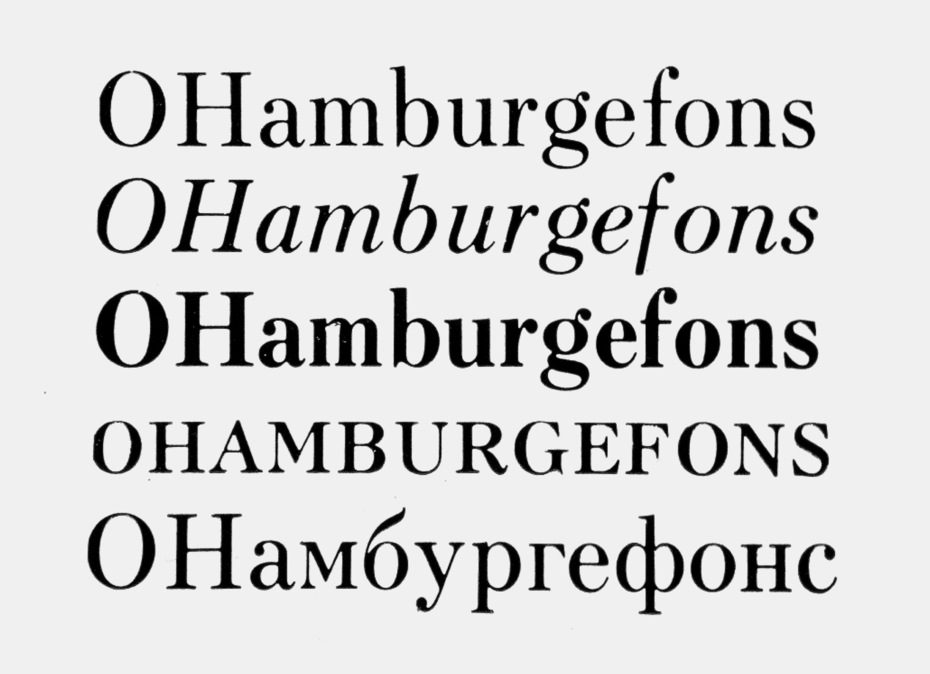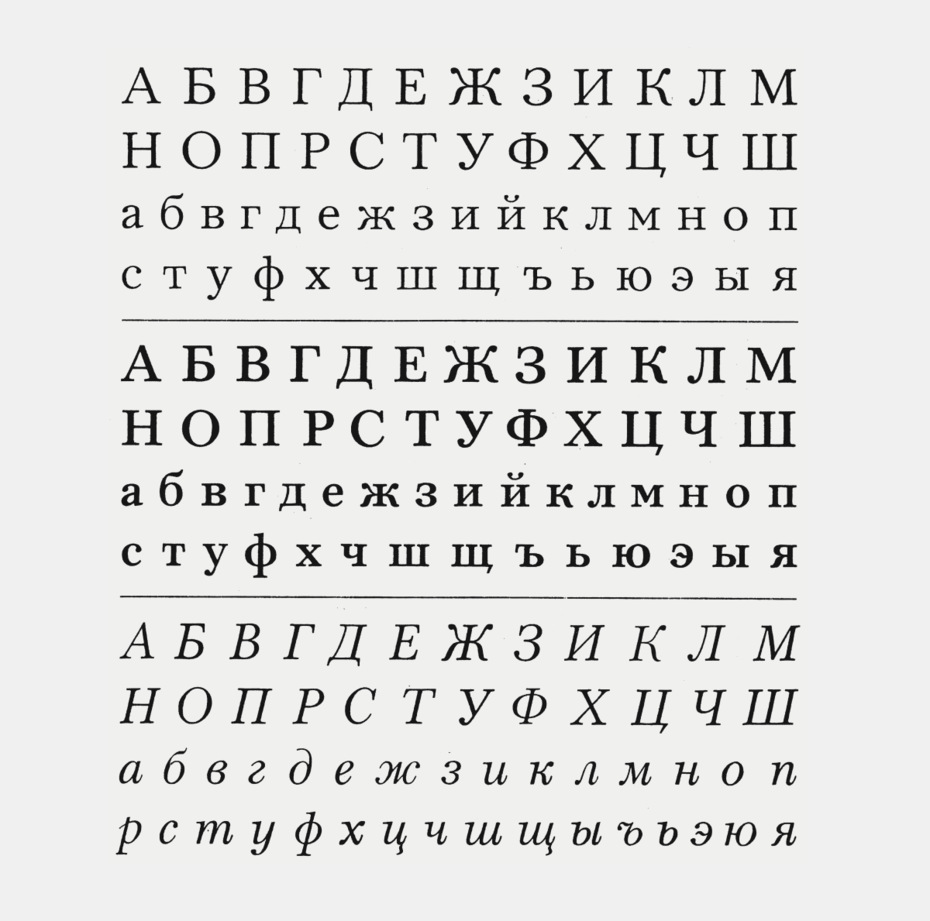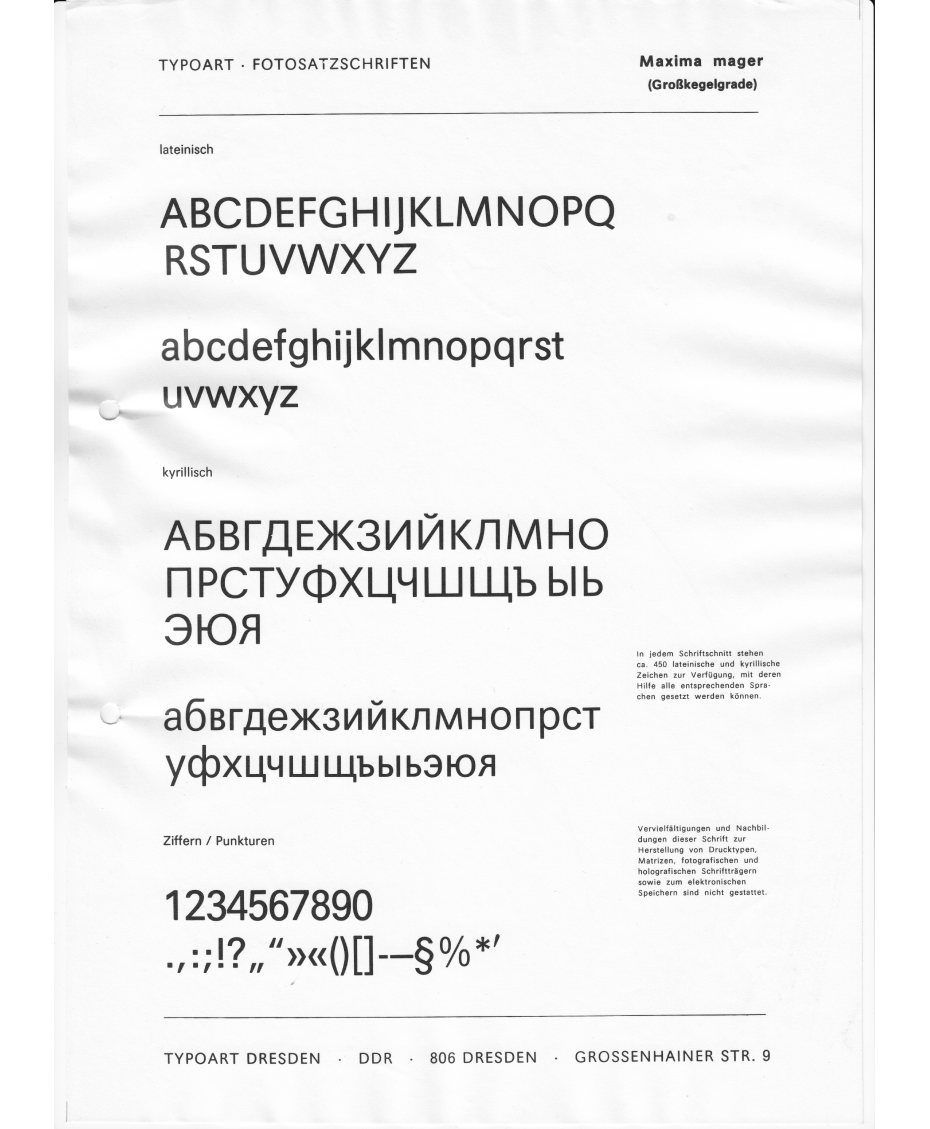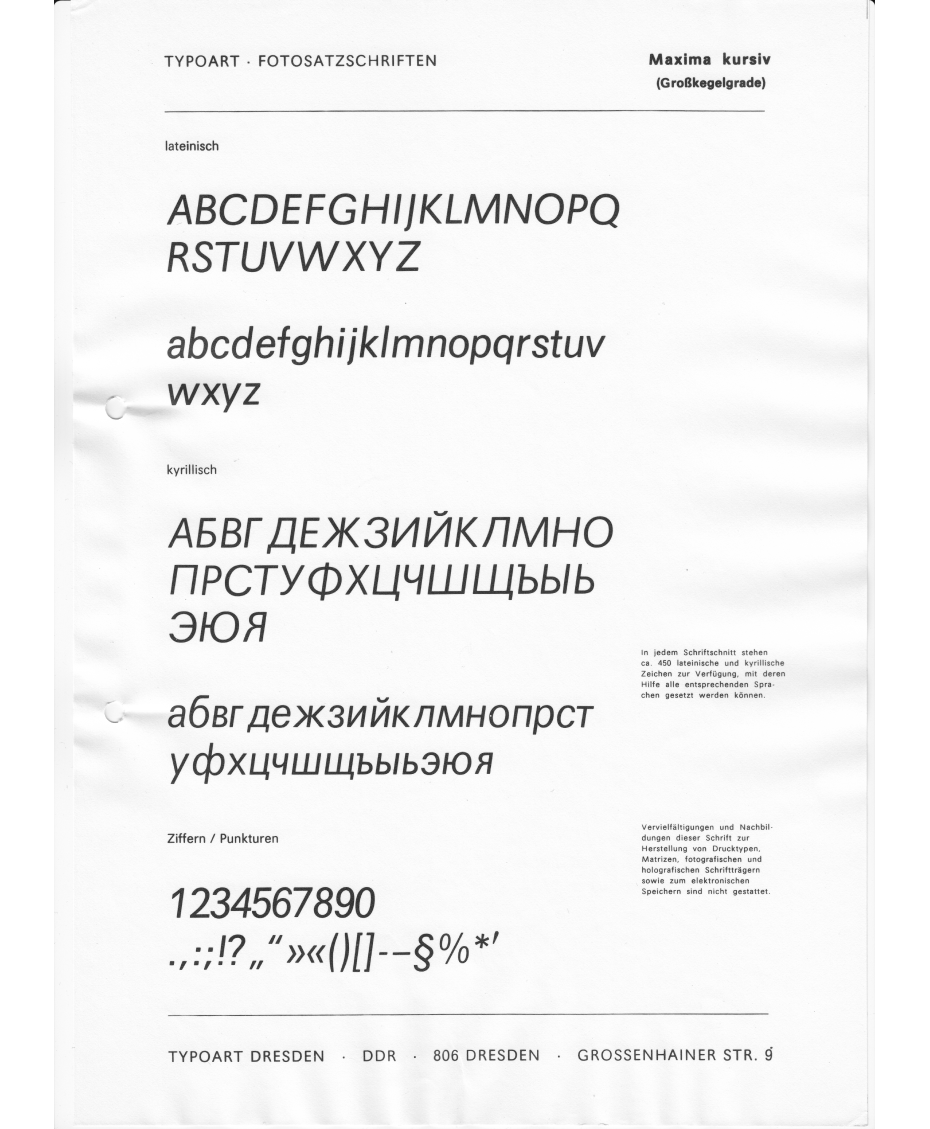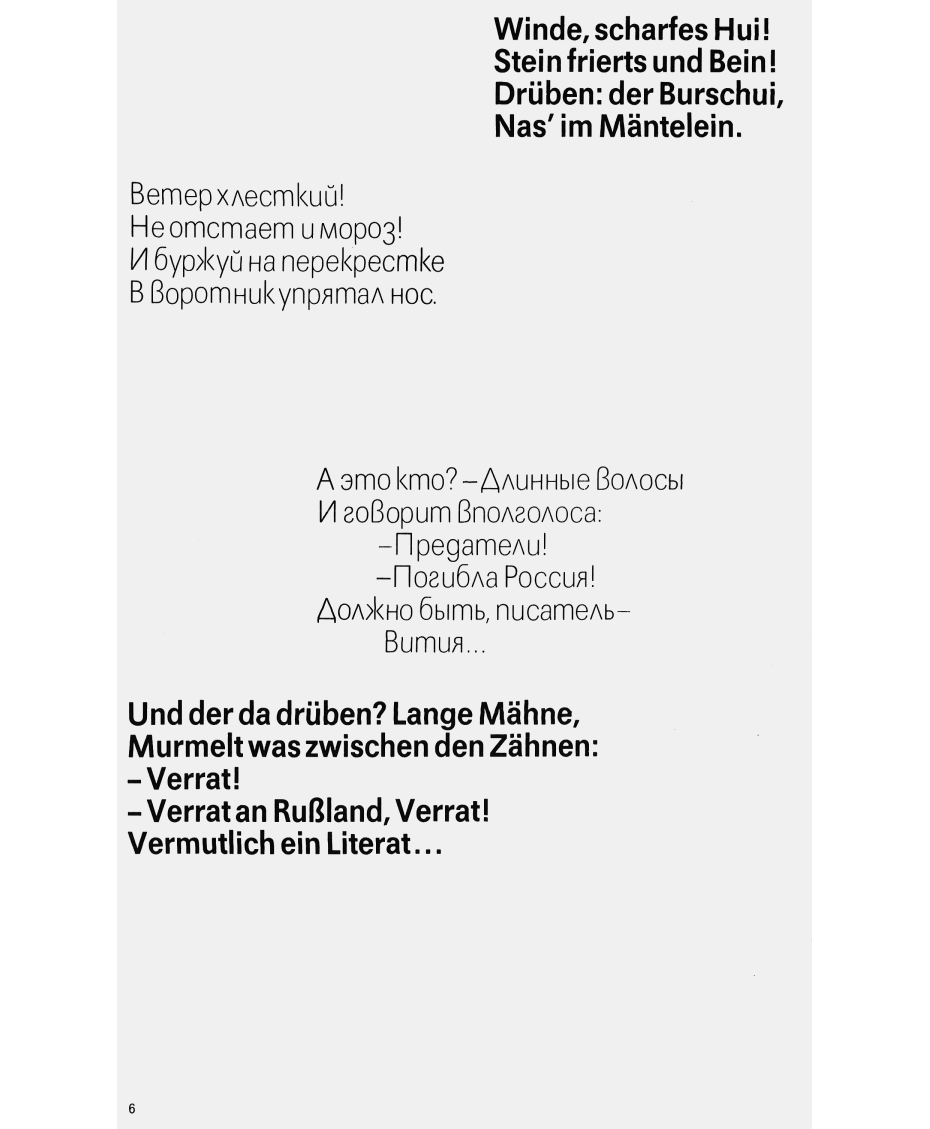
Из истории шрифтовых конкурсов. Часть 2
анр шриф­то­вых кон­кур­сов — ма­ло­изу­чен­ная об­ласть ис­то­рии гра­фи­че­ско­го ди­зай­на. Ди­зай­нер, ис­то­рик шриф­та Кон­стан­тин Го­лов­чен­ко дол­гое вре­мя ис­сле­до­вал ис­то­рию кон­кур­сов ки­рил­ли­че­ских шриф­тов и со­брал уни­каль­ные ар­хив­ные ма­те­ри­а­лы о шриф­тах-участ­ни­ках и ху­дож­ни­ках. Мы пуб­ли­ку­ем вто­рую часть его ис­сле­до­ва­ния: кон­кур­сы 1950−70-х го­дов сре­ди стран СЭВ и в Че­хо­сло­ва­кии. Сто­ит обра­тить вни­ма­ние, как мно­го ка­че­ствен­ных тек­сто­вых шриф­тов с ки­рил­ли­цей бы­ло при­сла­но на кон­курс, и мно­гие из них поз­же по­сту­пи­ли в про­из­вод­ство. При всём том, изу­чая со­вет­скую мас­со­вую пе­чать, мы ред­ко ви­дим эти шриф­ты в ра­бо­те — путь от про­ек­та до «ма­га­зин­ной пол­ки» (чи­тай — ти­по­гра­фии) ока­зы­вал­ся слиш­ком дол­гим, как это ча­сто бы­ва­ло и с дру­ги­ми ма­те­ри­аль­ны­ми объ­ек­та­ми ди­зай­на стран СЭВ. Ре­дак­ция
Часть I. Ка­кая ску­ка ри­со­вать шриф­ты
Часть II. «Ра­зо­ча­ро­вал Капр».
Кон­кур­с сре­ди стран — чле­нов СЭВ
Сле­ду­ю­щий се­рьёз­ный шриф­то­вой кон­курс, ко­то­рый мы рас­смот­рим, про­шёл в ГДР. При­уро­чен­ный к 500-ле­тию со дня смер­ти Иоган­на Гу­тен­бер­га, он был объ­яв­лен в фе­вра­ле 1968 г. и про­во­дил­ся сре­ди стран — чле­нов СЭВ. На кон­курс при­ни­ма­лись тек­сто­вые шриф­ты для на­бо­ра га­зет и жур­на­лов, тек­сто­вые шриф­ты для книж­но­го на­бо­ра (осо­бое вни­ма­ние уде­ля­лось шриф­там для на­бо­ра на­уч­но-тех­ни­че­ской ли­те­ра­ту­ры и школь­ных учеб­ни­ков), а так­же ак­ци­дент­ные шриф­ты.
Для под­го­тов­ки от­во­ди­лось три го­да — по­след­ним сро­ком от­прав­ки ра­бот бы­ло 1 фе­вра­ля 1971 г. По­бе­див­шие про­ек­ты пред­по­ла­га­лось ис­поль­зо­вать для со­зда­ния на­бор­ных шриф­тов для бук­во- и стро­ко­от­лив­ных ма­шин, а так­же фо­то­на­бо­ра — со­от­вет­ству­ю­щие тре­бо­ва­ния сле­до­ва­ло учи­ты­вать при раз­ра­бот­ке. Ри­сун­ки шриф­тов долж­ны бы­ли быть пред­став­ле­ны на двух бе­лых ли­стах го­ри­зон­таль­ной ори­ен­та­ции раз­ме­ром 50 × 70 см. На пер­вом ли­сте рас­по­ла­га­лись все про­пис­ные, строч­ные зна­ки и циф­ры обыч­но­го и по­лу­жир­но­го на­чер­та­ний, а так­же кур­си­ва. На вто­ром ли­сте нуж­но бы­ло вос­про­из­ве­сти над­пи­си OHamburgefons и «НХу­дож­ник-по­ли­гра­фист» во всех на­чер­та­ни­ях пред­став­ля­е­мо­го шриф­та.
На обрат­ной сто­ро­не всех ма­те­ри­а­лов про­став­ля­лось пя­ти­знач­ное чис­ло, ко­то­рое ду­бли­ро­ва­лось на при­ла­га­е­мом за­пе­ча­тан­ном кон­вер­те, со­дер­жа­щем имя и ад­рес участ­ни­ка. Кон­вер­ты мож­но бы­ло вскрыть толь­ко по­сле то­го, как жю­ри вы­не­сет окон­ча­тель­ное ре­ше­ние. Все ра­бо­ты, не удо­сто­ив­ши­е­ся на­град, бес­плат­но воз­вра­ща­лись их ав­то­рам.
От каж­дой стра­ны — чле­на СЭВ в со­став жю­ри вхо­ди­ло по два че­ло­ве­ка: спе­ци­а­лист по ху­до­же­ствен­ной ча­сти и тех­ни­че­ский экс­перт. До­пол­ни­тель­но име­лась воз­мож­ность на­пра­вить на­блю­да­те­лей с пра­вом со­ве­ща­тель­но­го го­ло­са.
Со­став жю­ри вы­гля­дел сле­ду­ю­щим об­ра­зом:
от Бол­га­рии: В. Йон­чев, про­фес­сор Ака­де­мии ху­до­жеств в Со­фии, и Г. Ко­лев, тех­ни­че­ский ру­ко­во­ди­тель шриф­то­ли­тей­но­го це­ха го­су­дар­ствен­ной ти­по­гра­фии «Г. Ди­мит­ров»;
от Че­хо­сло­ва­кии: Р. Му­рат (R. Murat), пред­се­да­тель Кон­суль­та­тив­но­го со­ве­та по со­зда­нию шриф­тов, и А. Рам­бо­усек (A. Rambousek), тех­ни­че­ский и ху­до­же­ствен­ный кон­суль­тант Го­су­дар­ствен­ной ти­по­гра­фии в Пра­ге;
от ГДР: Х. Э. Воль­тер (H. E. Wolter, пред­се­да­тель жю­ри), ху­до­же­ствен­ный и тех­ни­че­ский ди­рек­тор из­да­тель­ства Offizin Andersen Nexö в Лейп­ци­ге, и Х. Фи­шер (H. Fischer), опе­ра­ци­он­ный ди­рек­тор пред­при­я­тия VEB Typoart;
от Поль­ши: Р. То­ма­шев­ский (R. Tomaszewski), глав­ный спе­ци­а­лист по ти­по­граф­ским шриф­там Объ­еди­не­ния по­ли­гра­фи­че­ско­го про­из­вод­ства (ZPP), и Я. Шверч (J. Świerc), ди­рек­тор Фа­бри­ки по про­из­вод­ству ли­но­тип­ных мат­риц в Ка­то­ви­це;
от Вен­грии: Д. Хай­ман (G. Haiman), про­фес­сор Ака­де­мии при­клад­но­го ис­кус­ства в Бу­да­пе­ште, и И. Ко­жик (I. Kozsik), ру­ко­во­ди­тель Пер­вой вен­гер­ской сло­во­лит­ни, а так­же Э. Хедьи (É. Hegyi) в ка­че­стве на­блю­да­те­ля;
от СССР: В. В. Ла­зур­ский, ху­дож­ник, и П. Н. Бра­гин, на­чаль­ник мат­рич­но­го це­ха Лен­по­ли­граф­ма­ша, а так­же Е. И. Ильен­ко (глав­ный ху­дож­ник об­ще­ствен­но-по­ли­ти­че­ской ли­те­ра­ту­ры Ко­ми­те­та по пе­ча­ти при Со­ве­те Ми­ни­стров СССР и ру­ко­во­ди­тель со­вет­ской де­ле­га­ции) и Р. Г. Але­ев (ди­рек­тор из­да­тель­ства «Изоб­ра­зи­тель­ное ис­кус­ство») в ка­че­стве на­блю­да­те­лей.
Все эти лю­ди не мог­ли участ­во­вать в кон­кур­се лич­но, хо­тя один из кон­кур­сан­тов — Аль­берт Капр — вы­сту­пал в ро­ли кон­суль­тан­та жю­ри.
Для по­бе­ди­те­лей был пре­ду­смот­рен со­лид­ный при­зо­вой фонд. В ка­те­го­рии тек­сто­вых шриф­тов за два пер­вых ме­ста вы­пла­чи­ва­лось по 4000 ₽, за два вто­рых — по 3500 ₽, за два тре­тьих — по 3000 ₽, кро­ме то­го, бы­ло две пре­мии по 1500 ₽. В ка­те­го­рии ак­ци­дент­ных за два пер­вых ме­ста — по 1500 ₽, за два вто­рых — по 1250 ₽, за два тре­тьих — по 1000 ₽ плюс две пре­мии по 750 ₽. Вы­пла­ты про­из­во­ди­лись по офи­ци­аль­но­му кур­су в ва­лю­те со­от­вет­ству­ю­щей стра­ны. Для ори­ен­ти­ра: в 1971 г. це­на ав­то­мо­би­ля ВАЗ-21011 «Жи­гу­ли» со­став­ля­ла 5620 ₽, а ав­то­мо­би­ля ЗАЗ-966 «За­по­ро­жец» — 3000 ₽.
Ин­те­рес­но, что в СССР, по­ми­мо это­го, ху­дож­ни­ки по­лу­ча­ли оп­ла­чи­ва­е­мые за­да­ния на раз­ра­бот­ку кон­курс­ных про­ек­тов. Для под­го­тов­ки к кон­кур­су бы­ли при­вле­че­ны От­дел глав­но­го ху­дож­ни­ка Ко­ми­те­та по пе­ча­ти при Со­ве­те Ми­ни­стров СССР и От­дел но­вых шриф­тов ВНИ­И­О­ПИ­Та, а так­же цен­траль­ные из­да­тель­ства. Ру­ко­вод­ство этой про­грам­мой осу­ще­ствлял за­ме­сти­тель пред­се­да­те­ля Ко­ми­те­та по пе­ча­ти Н. И. Спих­ну­лин. В От­де­ле но­вых шриф­тов это оформ­ля­лось как раз­ра­бот­ка те­мы (Га­ли­на Бан­ни­ко­ва, на­при­мер, не­смот­ря на своё же­ла­ние за­ни­мать­ся со­зда­ни­ем но­во­го шриф­та для кон­кур­са, со­гла­сия на это не по­лу­чи­ла). Был со­здан орг­ко­ми­тет и от­бо­роч­ная ко­мис­сия, где про­смат­ри­ва­лись все от­сы­ла­е­мые на кон­курс ра­бо­ты, ока­зы­ва­лась по­мощь в пра­виль­ном оформ­ле­нии про­ек­тов. При этом осо­бо по­ощря­лось со­зда­ние уни­вер­саль­ных гар­ни­тур. Пи­ка ак­тив­но­сти эти под­го­то­ви­тель­ные ра­бо­ты до­стиг­ли в по­след­ние не­сколь­ко ме­ся­цев.
Вто­рая пре­мия бы­ла при­су­жде­на ра­бо­там Ста­ни­сла­ва Мар­шо и Пав­ла Тей­ме­ра. Жю­ри вы­со­ко оце­ни­ло их вы­со­кий тех­ни­че­ский уро­вень и со­от­вет­ствие за­да­нию. От­ме­ча­лось, что шрифт Мар­шо прак­ти­че­ски пол­но­стью ли­шён де­ко­ра­тив­ных эле­мен­тов, прав­да, кур­сив в этом от­но­ше­нии не­иде­а­лен. В этом про­ек­те бы­ло ре­ко­мен­до­ва­но пе­ре­ра­бо­тать не­ко­то­рые ма­те­ма­ти­че­ские сим­во­лы и бук­вы, что­бы они луч­ше вы­де­ля­лись при на­бо­ре.